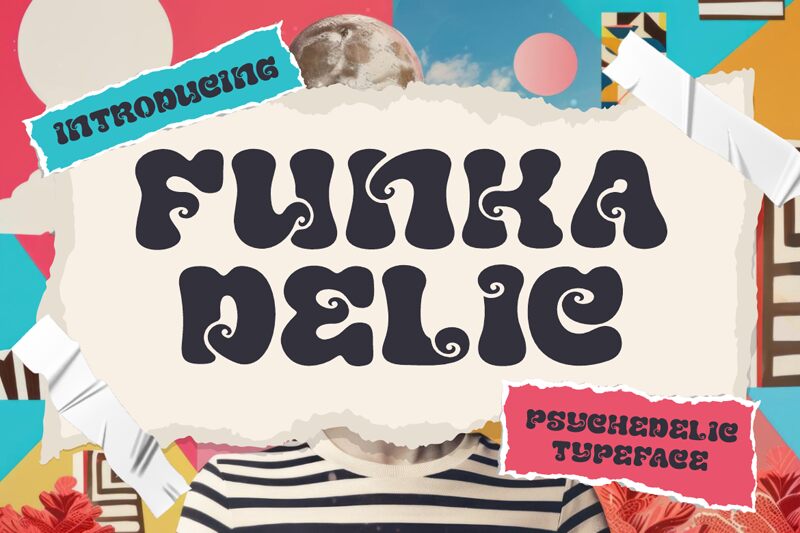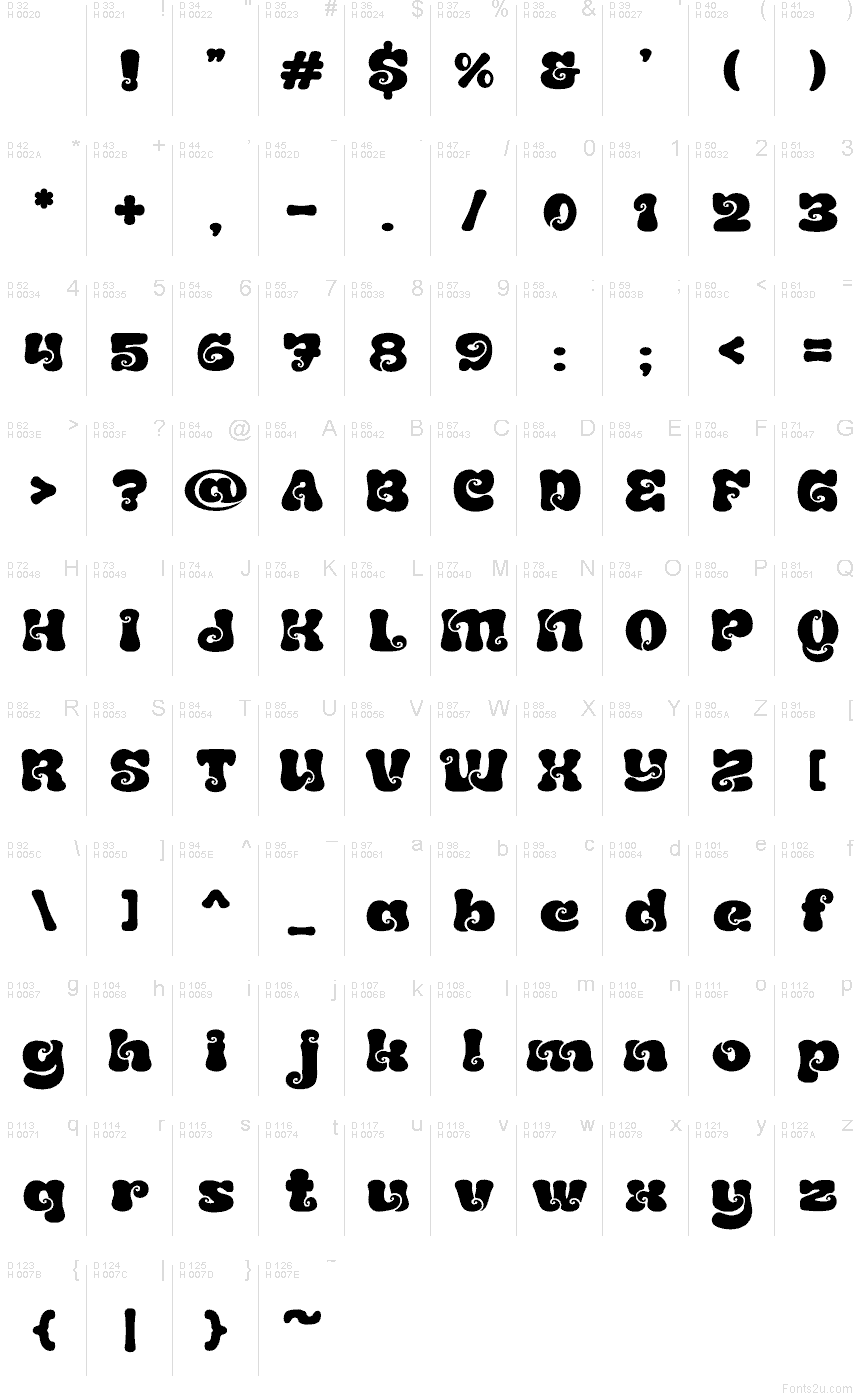
Funkadelic
Shanaf Studioが手がけた「Funkadelic」は、サイケデリックな躍動感あふれる無料のグルーヴィーなディスプレイフォントです。文字は太く、とろけるようなシルエットに膨らみ、最後はキュッと締まった渦巻き状のカールで終わります。まるで60年代後半のポスターカルチャーを彷彿とさせる「ラバライト」のようなリズムを持ちながらも、決してくどさを感じさせないデザインです。
音楽イベントのポスター、レトロなブランドロゴ、アルバムジャケット、フェスティバルのグラフィック、そして遊び心あふれるパッケージデザインなど、フォント自体がムードを物語るような作品に最適です。無料フォントですので、短い見出しやタイトルカード、ロゴのスケッチにも活用でき、特にその大きく丸みを帯びたフォルムと渦巻くディテールが活きる場面で真価を発揮します。